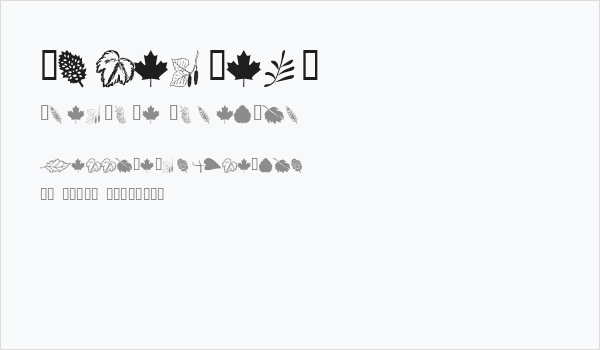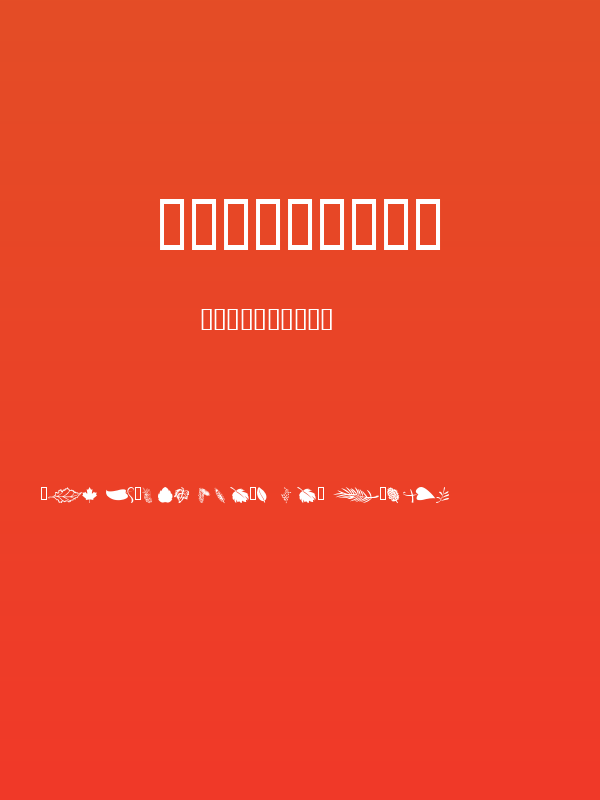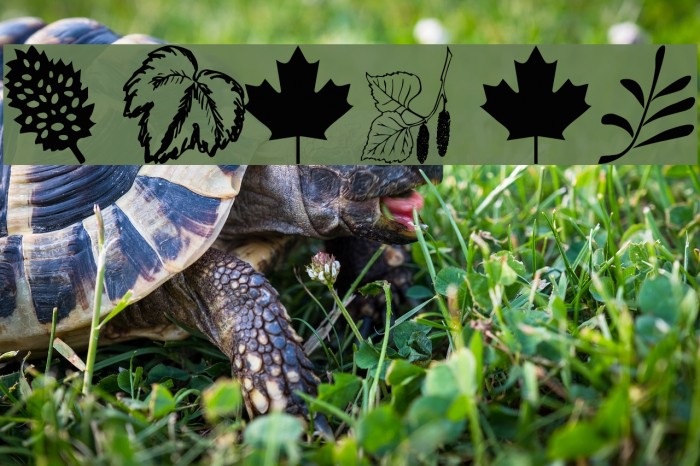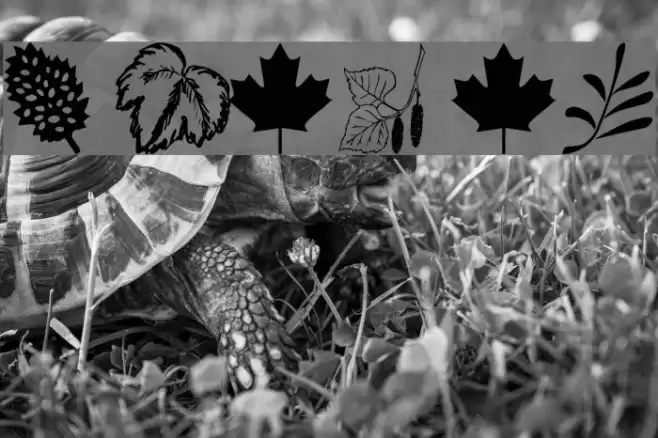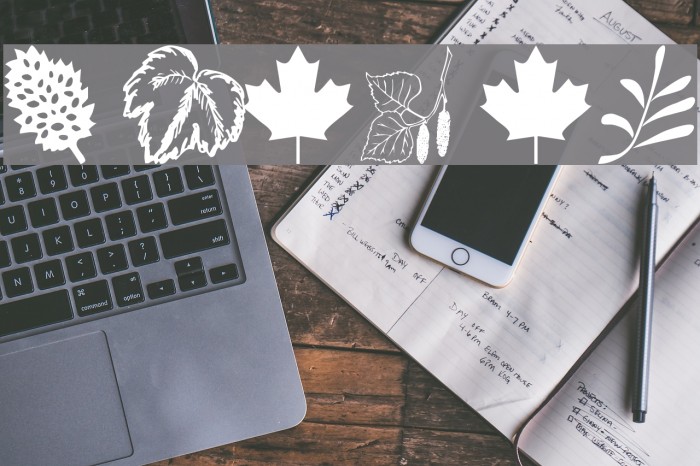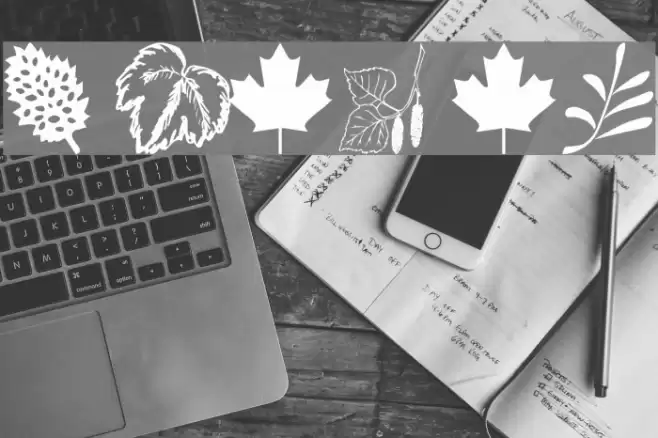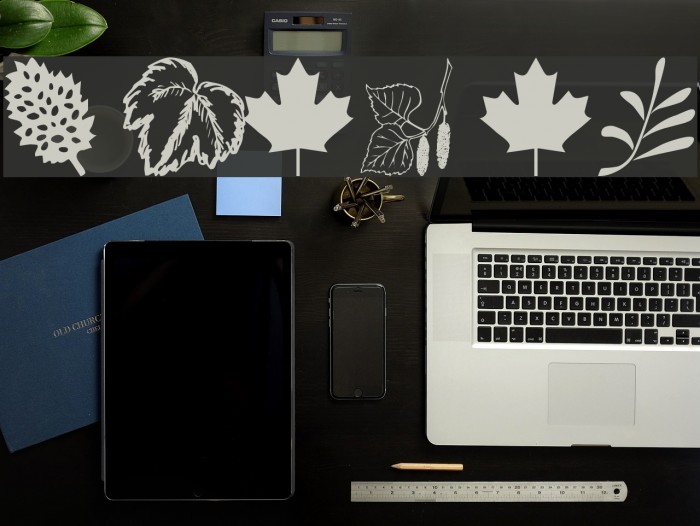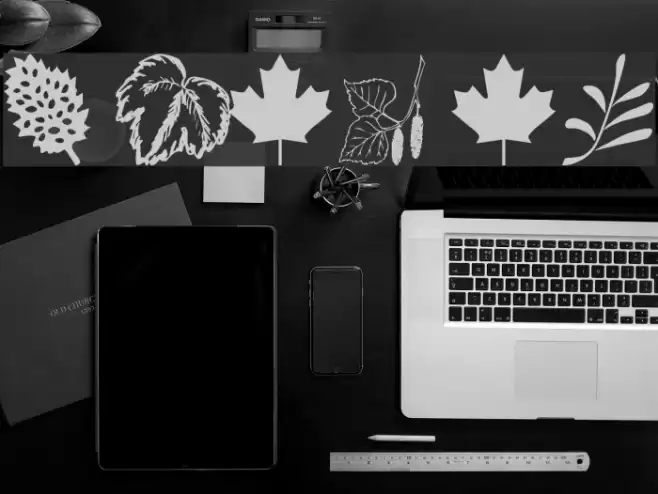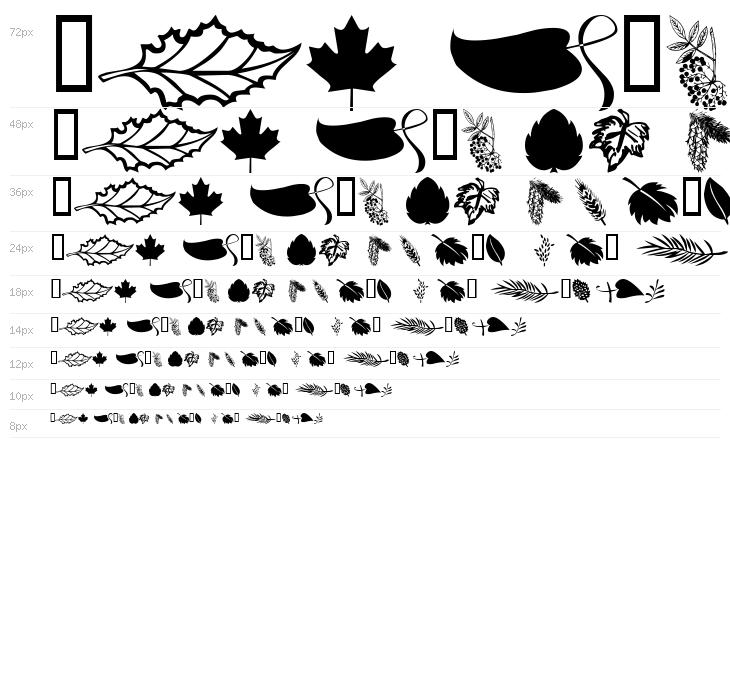
wmleaves1 Font
| 全体的なスタイル | Decorative, Nature-inspired |
| 用途 | Logos, Decorative elements, Themed graphics, Scrapbooking |
| おすすめプロジェクト | Nature-themed invitations, eco-friendly branding, seasonal graphics, scrapbooking, decorative dividers, and educational materials. |